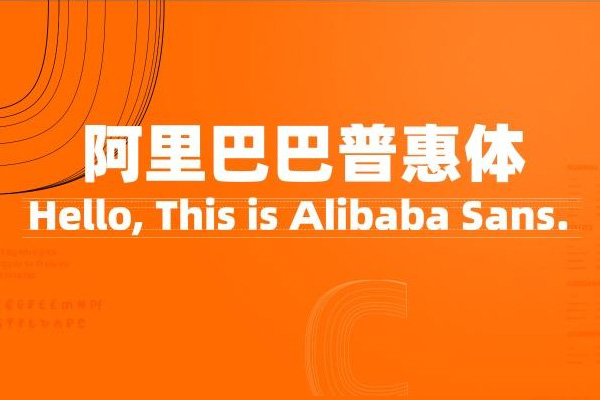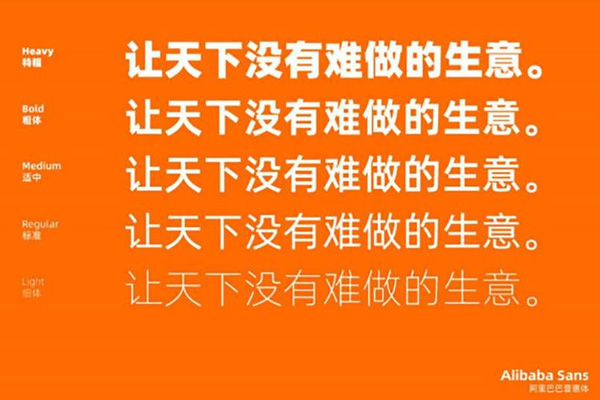
阿里巴巴普惠体
阿里巴巴推出的一款免费字体,首款企业发布免费字体,赢得了众多好评。当然,也引起了一些争议。不过,作为一款免费且可商用的字体,它确实出色。该字体包含五种不同的字重,字符齐全,字形与微软雅黑和思源黑体相似。它的推出不仅赚足了口碑,也为广大设计师提供了更多的选择。
这款字体的推出,不仅体现了阿里巴巴对设计领域的关注和支持,也为推动免费字体的普及和发展做出了积极贡献。虽然有些人对这款字体持不同意见,但它的出现无疑为设计师们带来了更多的选择余地,同时也为推动字体设计领域的创新和发展起到了积极的推动作用。
阿里巴巴普惠体效果预览
阿里巴巴普惠体字体效果预览